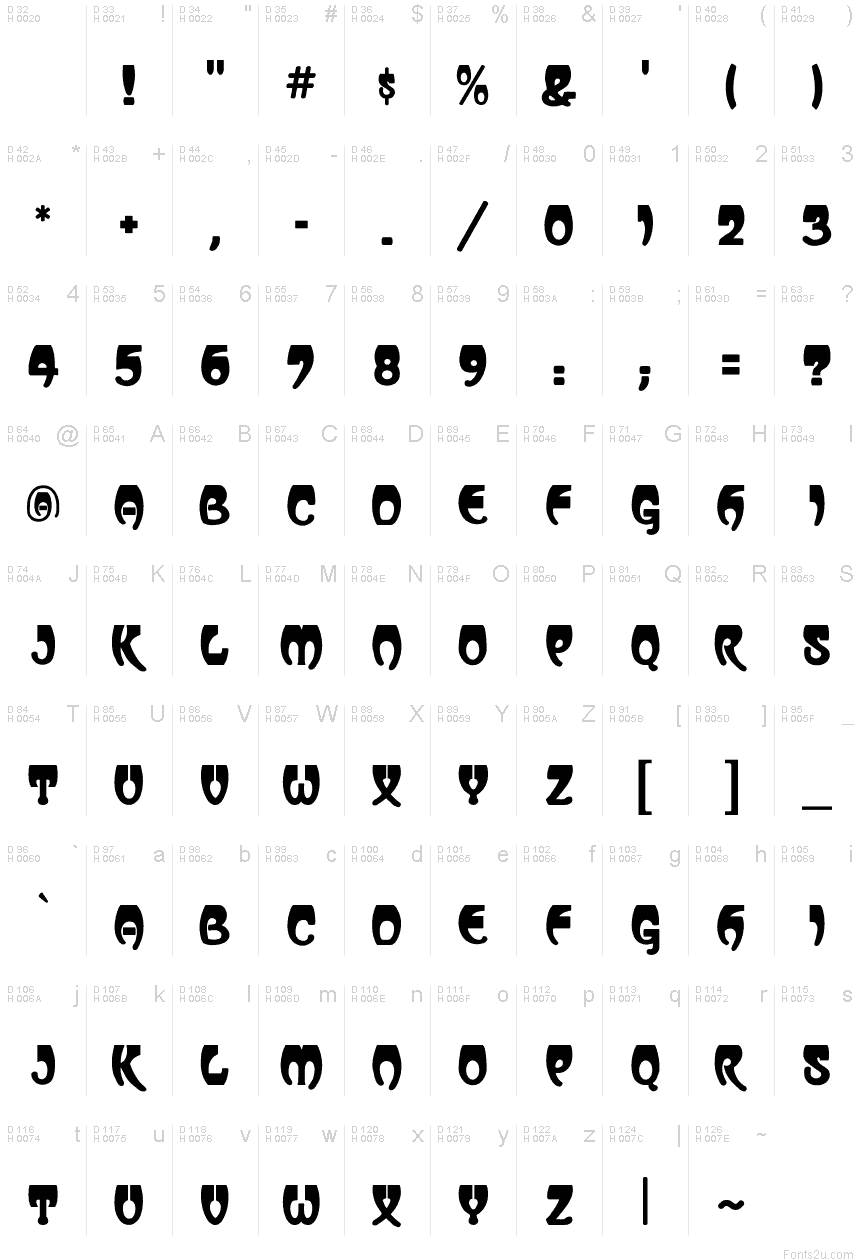
Vassar Regular 字体
Vassar Regular
由 Richard William Mueller 设计的 Vassar 是一款免费的、具有浓郁 70 年代风格的嬉皮风标题字体,其字形饱满且流畅。它宽大的笔画曲线收窄为纤细的连接处,重复出现的泪滴状开口和微小的矩形切口,让字母看起来更像是雕刻出来的,而非绘制而成。
它可以让标题成为画面的一部分,特别适合围绕迷幻曲线或熔岩灯形态构建的音乐海报、唱片包装和复古活动图形。其同样圆润的体量和不寻常内部形态也很适合时尚品牌塑造和周边商品,通过即使没有额外装饰也能一眼辨认的趣味时代感,将这些不同的应用场景串联起来。